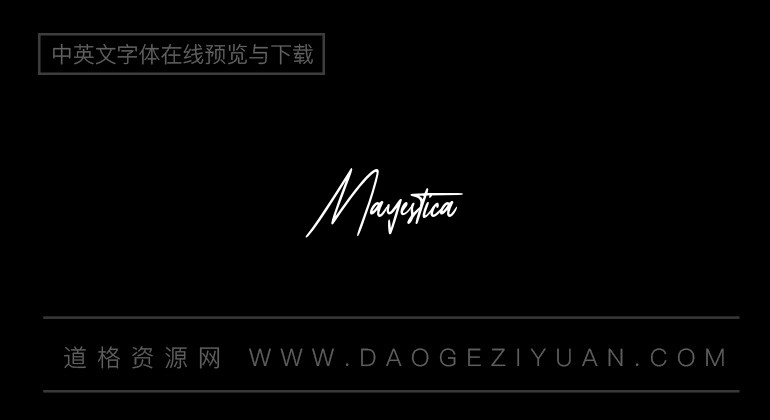
? Mayestica 字体是一款由著名设计师Maya Eilam设计的新字体,它具有独特的设计风格,拥有清晰的线条和优美的曲线,使字体看起来更加精致和现代。它让文字充满活力,具有较强的表现力,可以满足不同的设计需求。内容介绍
Mayestica是一款非常不错的手写艺术字体,具有很好的视觉感,适合于文化类的宣传设计、商业类品牌的广告和产品包装设计以及个性化文字排版等较多场景。